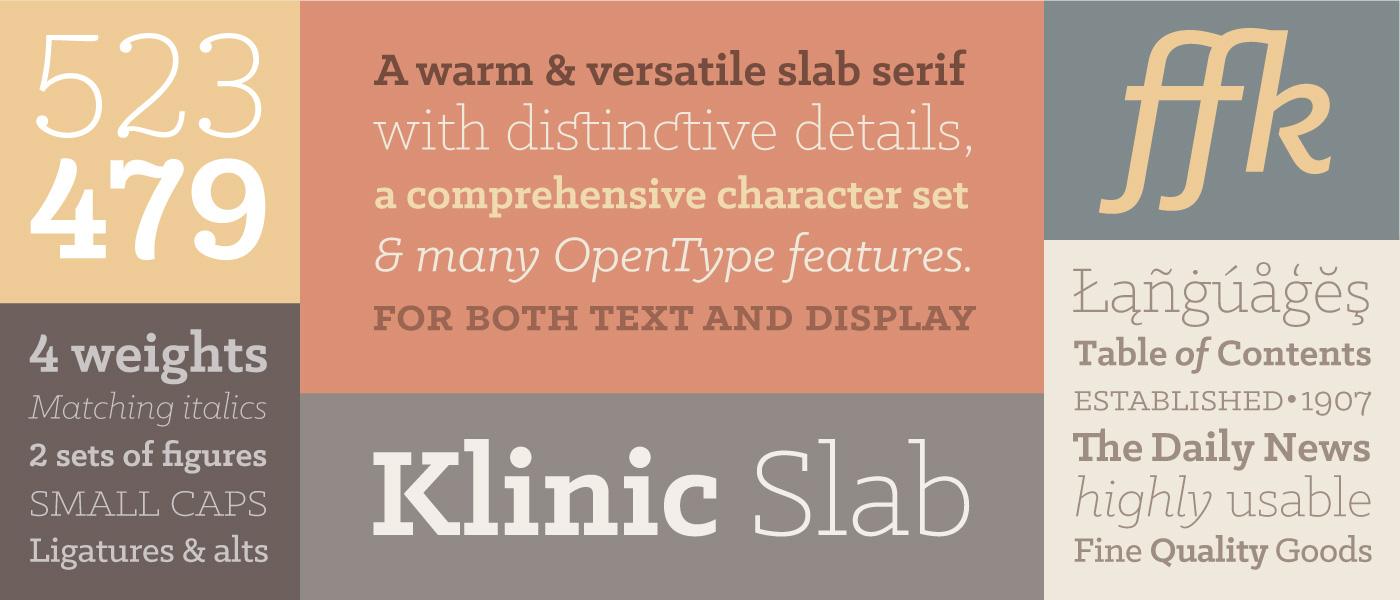
Webfont – und wenn ja, welcher …?
ich bräuchte mal bitte eure Meinung und Erfahrung auf einem Gebiet, wo ich mich (noch) nicht so gut entscheiden kann:
Meine „Hausschrift“ ist die Klinic Slab (Lost Type), die ich bisher für meine gesamte Kommunikation nutze. Demnächst möchte ich mich an meine Website machen und stelle mir nun die Frage, ob ich diese Schrift auch hier für alles (Headlines, Fließtext, Navigation) nutzen sollte/kann oder ob hierfür eine serifenlose Schrift geeigneter wäre? Immerhin soll man die Website ja auch auf dem kleinen Mobile-Monitor lesen können und ich kann mich erinnern, dass mir mal jemand gesagt hat, für Websites wählt man besser eine serifenlose Schrift. Wobei es ja hier im Forum auch komplett mit Serifen gelöst ist.
Und wenn ich nun eine serifenlose Schrift einsetze (was ich mir auch gut vorstellen könnte), welche würde eurer Meinung nach gut dazu passen? Habt ihr eine Empfehlung: lieber direkt vom Server der Website oder einen Font-Hosting-Dienst wie z. B. Google-Fonts?
Ja, du kannst heutzutage problemlos auch eine Slab wie die Klinic im Web benutzen.
Damit wir alle wissen, worum es geht …
Ich werde es zunächst versuchen, ausschließlich die Klinic auf der Website einzusetzen, bin aber vorerst noch nicht ganz sicher, ob es mir gefällt. Hat denn evtl. noch jemand einen Tipp, welche Sans vielleicht doch in Kombination fürs Web dazu passen könnte?